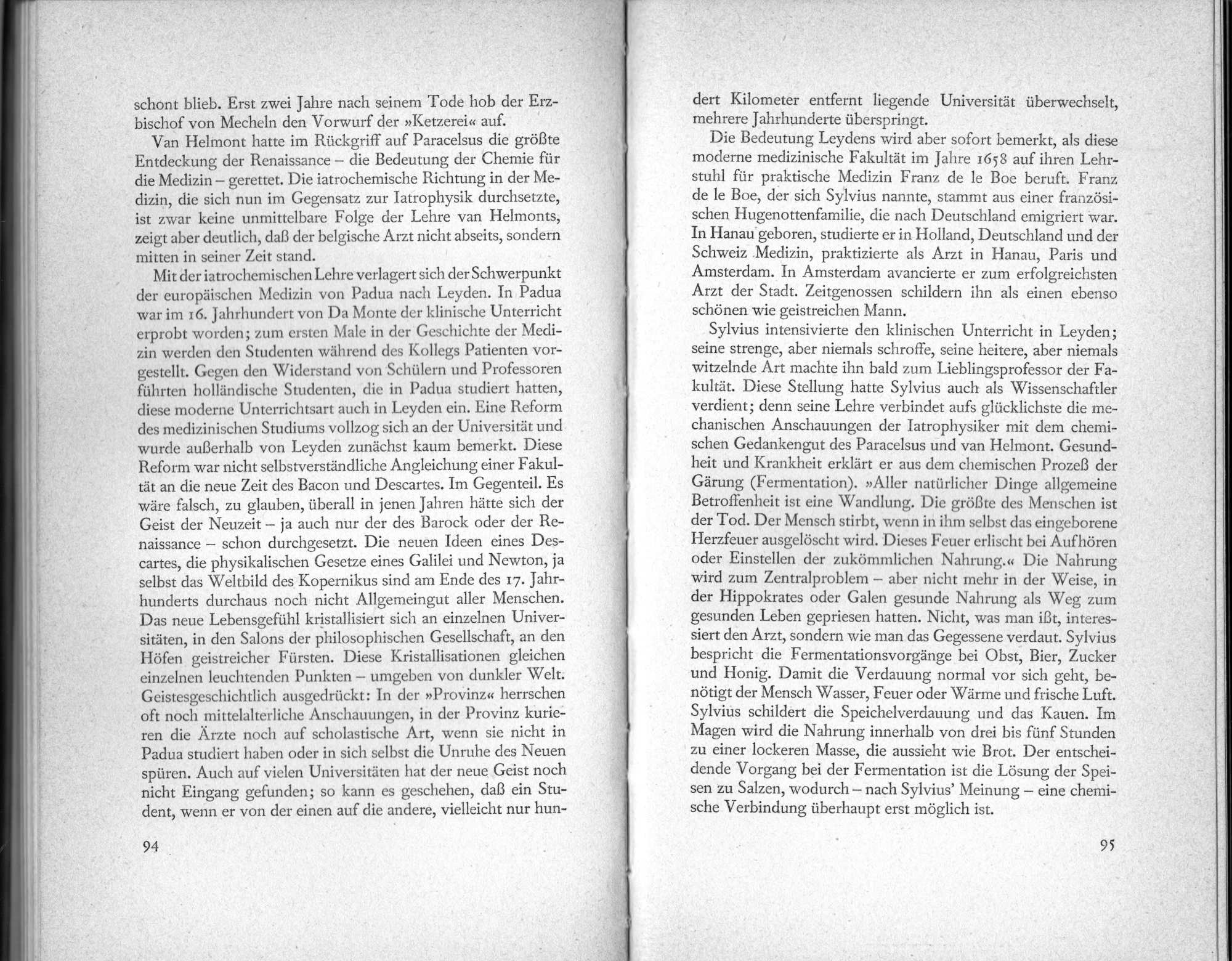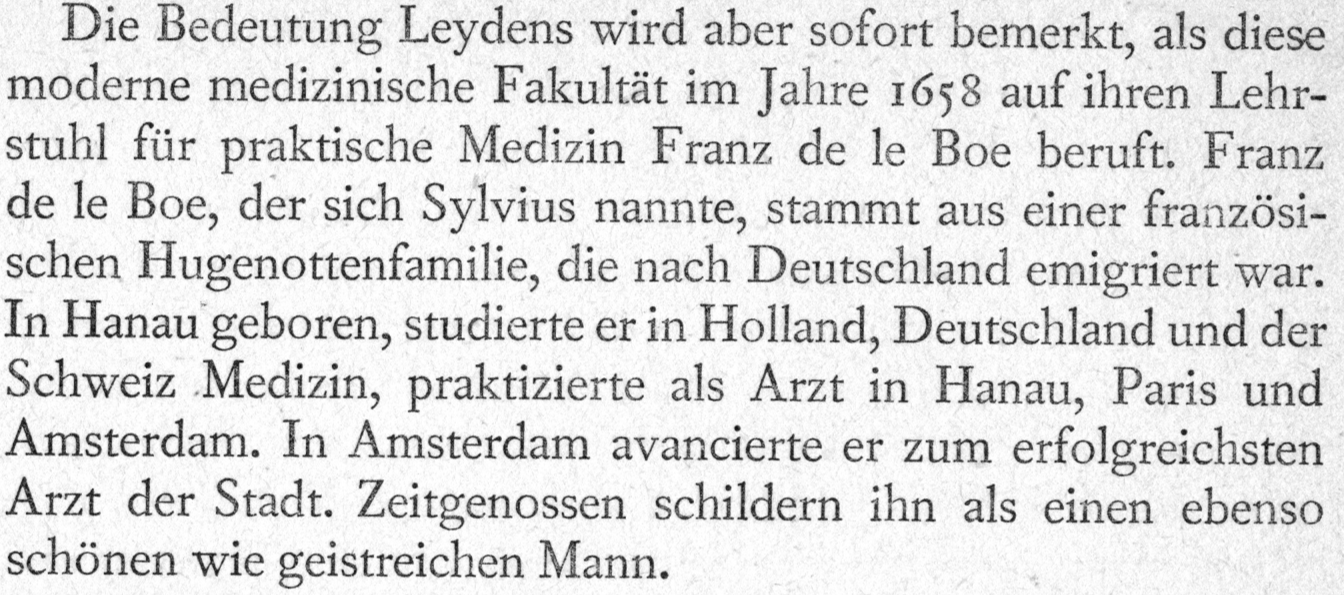
Welche Font/Schriftart ist das? Verlag Heinrich Scheffler
ich suche schon sehr lange nach dieser Schriftart, die ich in einem Buch von 1956 aus dem Verlag Heinrich Scheffler entdeckt habe (siehe angehängte Dateien). Hat jemand von euch eine Idee, welche es sein könnte?
es sieht nach Monotype Fournier aus. Also müsste das Buch im Monotype-Verfahren gesetzt werden. Es gibt eine digitale Version der Schrift sowie weitere digitale Fonts am Markt (auch OpenSource Fonts wie Charter und Source Serif), die sich auf den Schriften von Pierre-Simon Fournier le jeune (1712–1768) basieren.